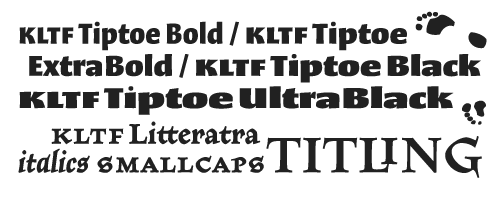
KLTF ist die Online Font Foundry von Karsten Lücke, Village-Mitglied und ehemaliger Typostammtisch-Besucher. Der erste offizielle Demofont von KLTF steht zum Download bereit: Tiptoe Toy. Tiptoe Toy ist ein Versalfont in vier Gewichten, die in InDesign CS2 über die OpenType-Features »Formatsätze« aufgerufen werden. Details gibt es auf der Website und in der beiliegenden Anleitung!
Tiptoe und Litteratra haben kleine Geschwister bekommen – die Basic-Varianten. Wem die OpenType-Spielereien zuviel sind, bieten die Basic-Varianten einen PST1-ähnlichen Zeichensatz, jedoch mit allen Akzentbuchstaben eines Pro OpenType-Font.